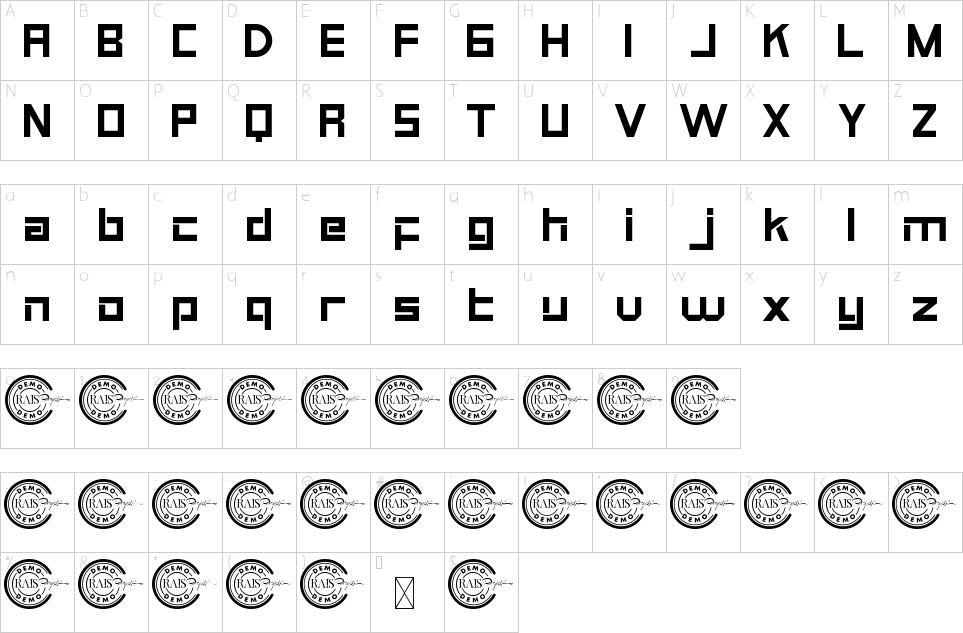
A página ‘Grandness Font – 1001 Free Fonts’ apresenta uma excelente oportunidade para designers apaixonados por fontes grátis. Desenvolvida pelo designer não informado, a font Grandness é um recurso valioso para quem busca uma fonte única e moderna sem precisar pagar. Esta font foi projetada especialmente para Windows e Mac, oferecendo o máximo de versatilidade ao designer. Com seu design cuidadosamente elaborado por raisproject, ela já recebeu mais de mil downloads, demonstrando sua popularidade entre os amantes de recursos gratuitos. Adicionar a Grandness à sua coleção pode tornar seus projetos ainda mais impressionantes e personalizados. Ela é ideal para aplicações que exigem uma aparência elegante e sofisticada, dando um toque único ao seu trabalho. Como parte do catálogo vasto de 1001 Free Fonts, Grandness é uma escolha ótima para aqueles buscando recursos para projetos de design sem comprometer o orçamento.